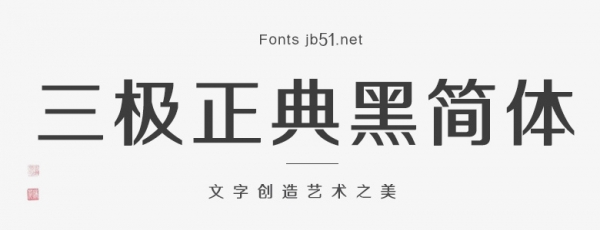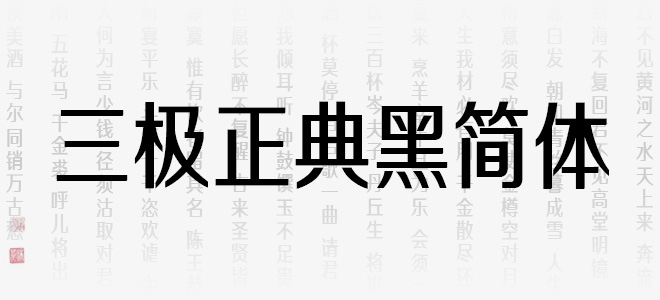
三極正典黑簡體作品整體風(fēng)格鮮明方正,字體結(jié)構(gòu)干練簡潔穩(wěn)重大氣,筆畫平直、豎粗橫細(xì),撇捺鏡像對稱穩(wěn)健。起筆收筆平直,折、鉤轉(zhuǎn)折明顯,圓潤飽滿。它的靈感來源于黑體,又富有變化,給人一種莊重的感覺,具有婉轉(zhuǎn)柔和的氣質(zhì)。視覺效果簡潔易識別,實(shí)用性強(qiáng)。本作品適用于傳統(tǒng)印刷媒介的標(biāo)題與正文排版、各類屏幕顯示及影視字幕等。
三極正典黑簡體